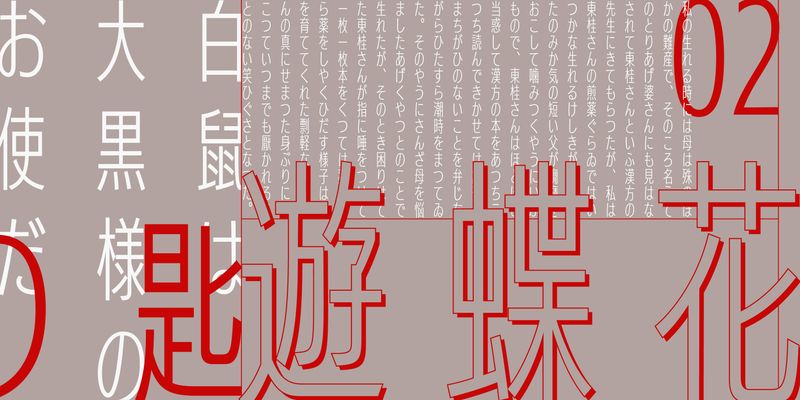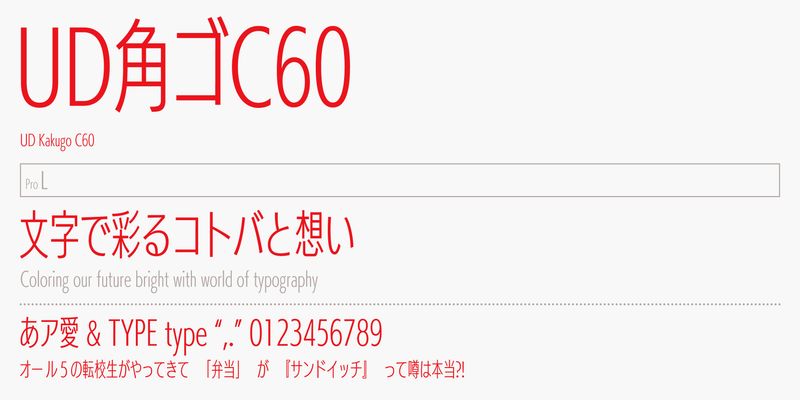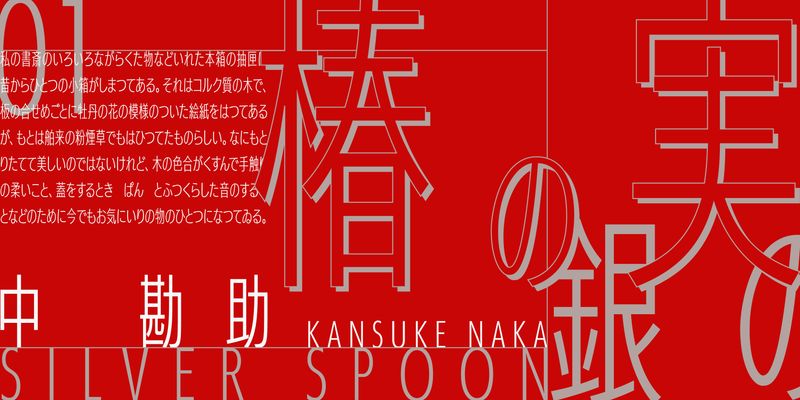
Um eine große Menge an Informationen auf begrenztem Raum lesbar und schön darzustellen, wurde diese Schrift mit 60% der Breite der UDKakugo_Large entworfen. Sie kann effektiv zur Darstellung von Bildunterschriften und Hinweisen in kleineren Größen verwendet werden.